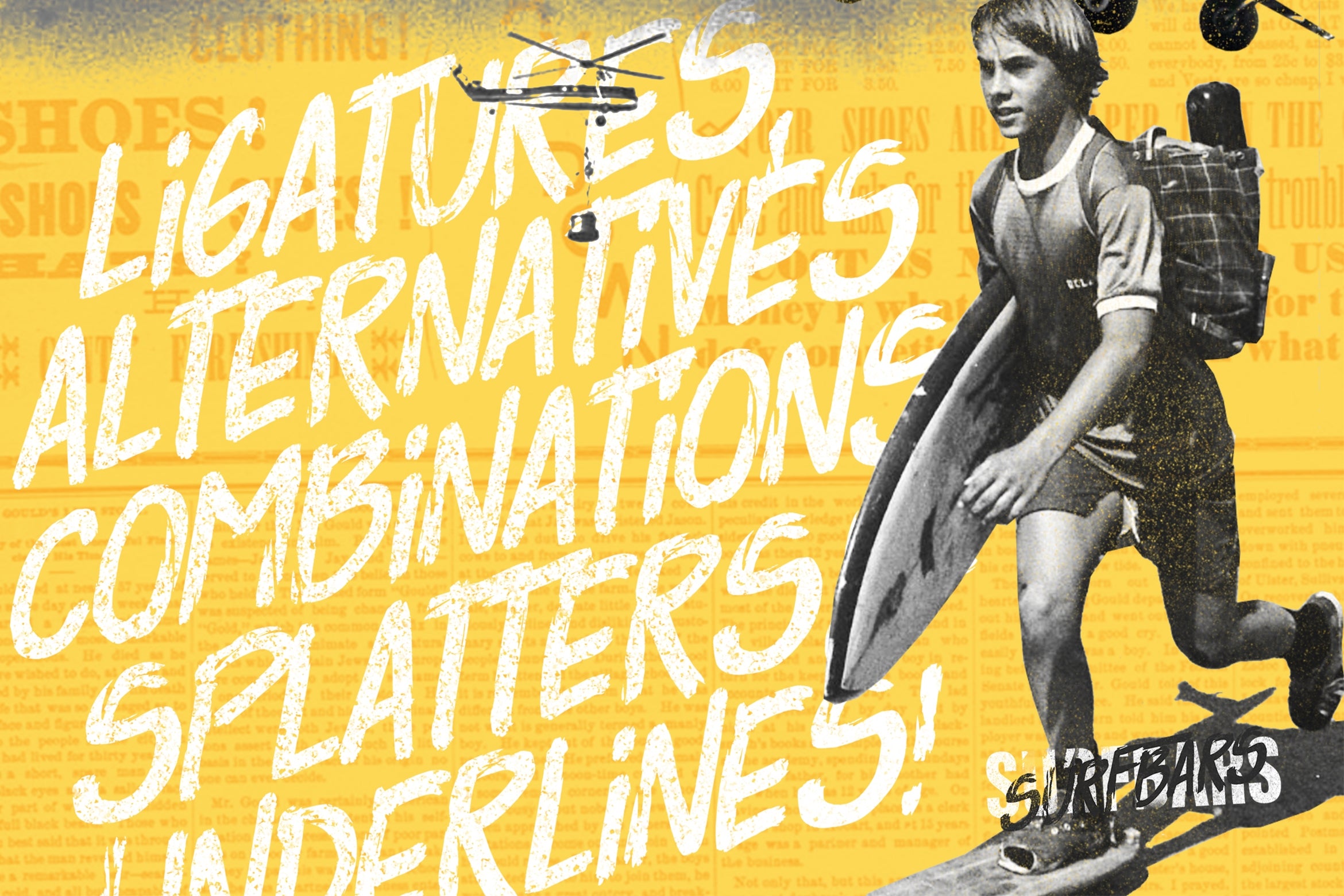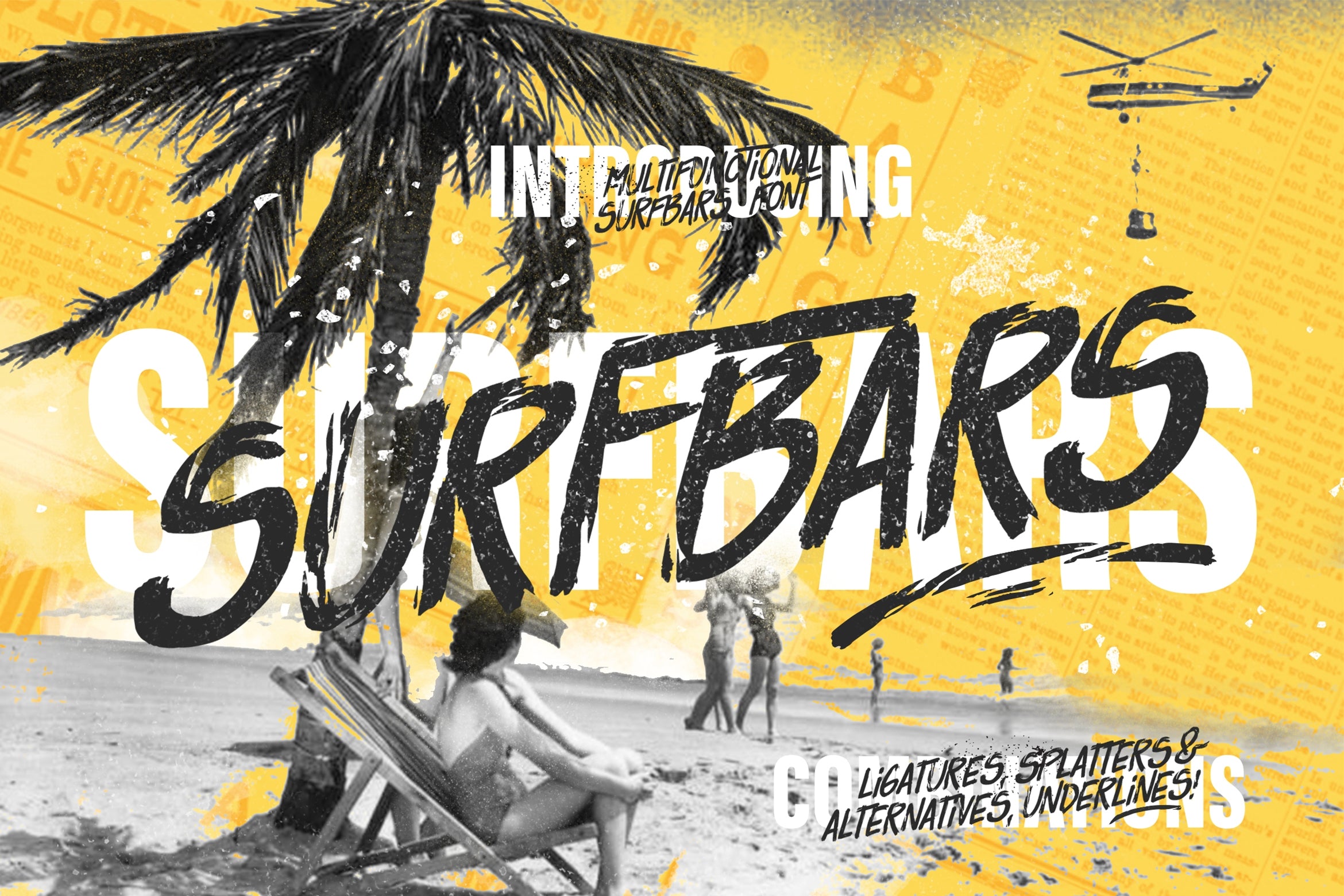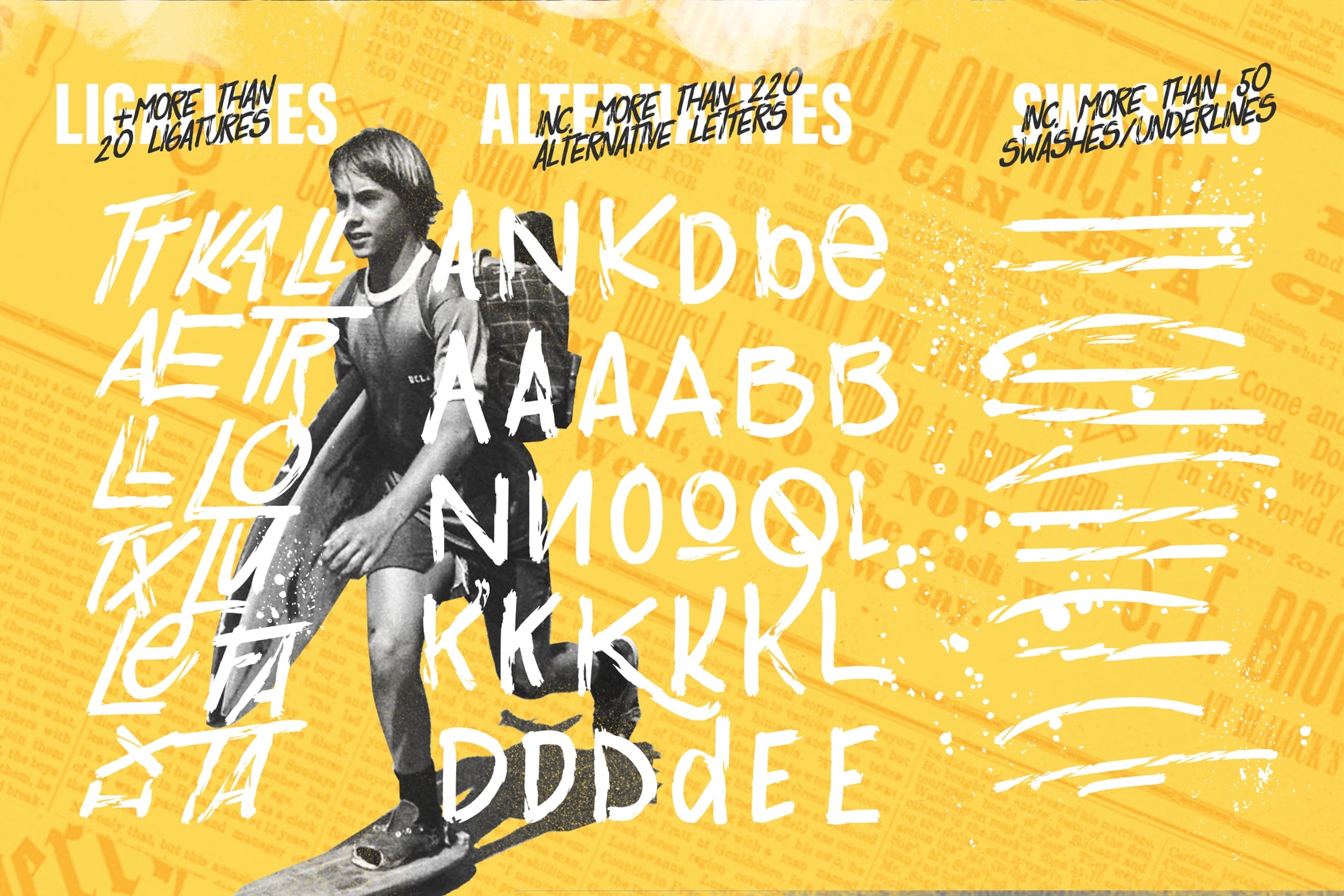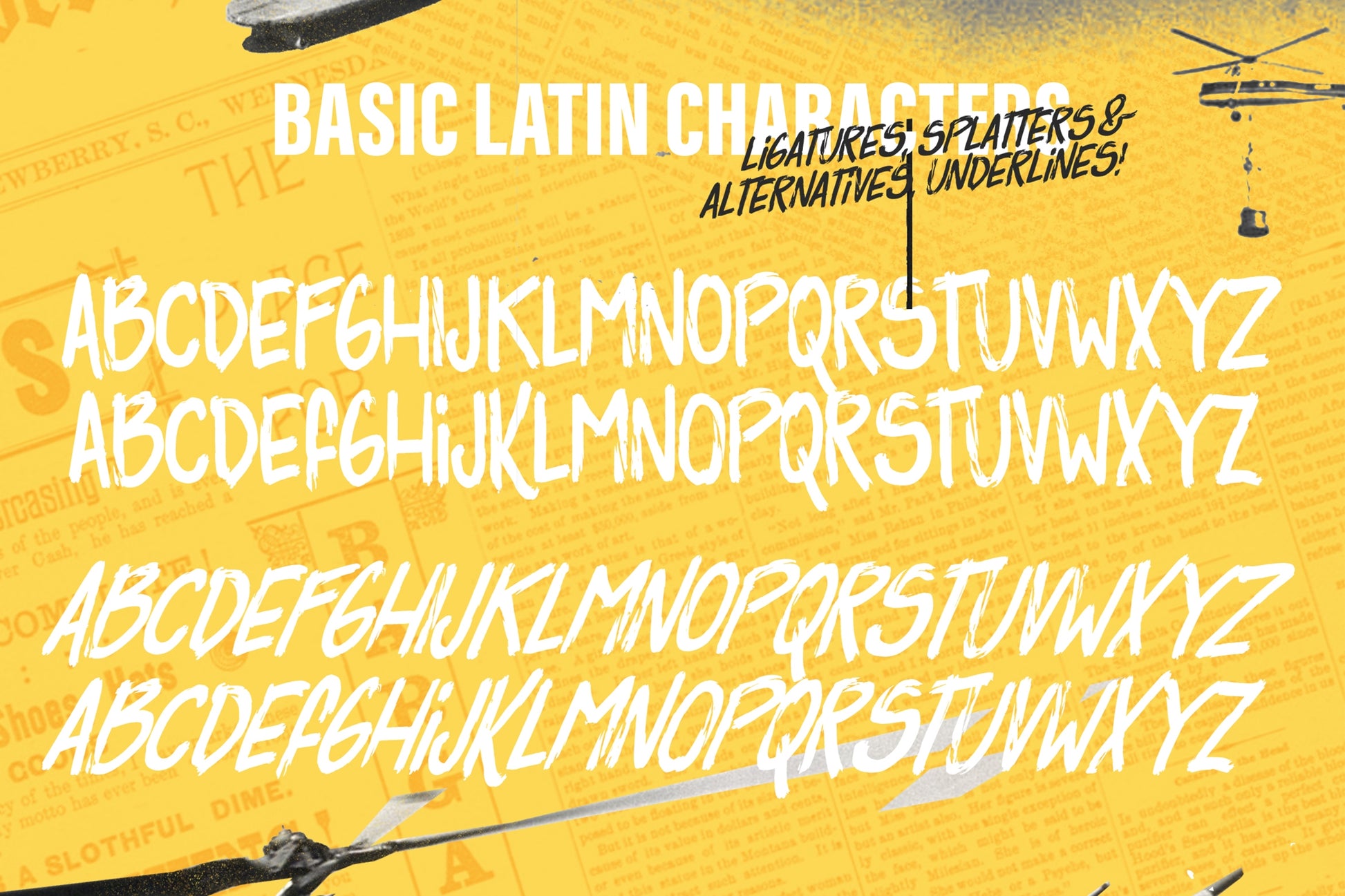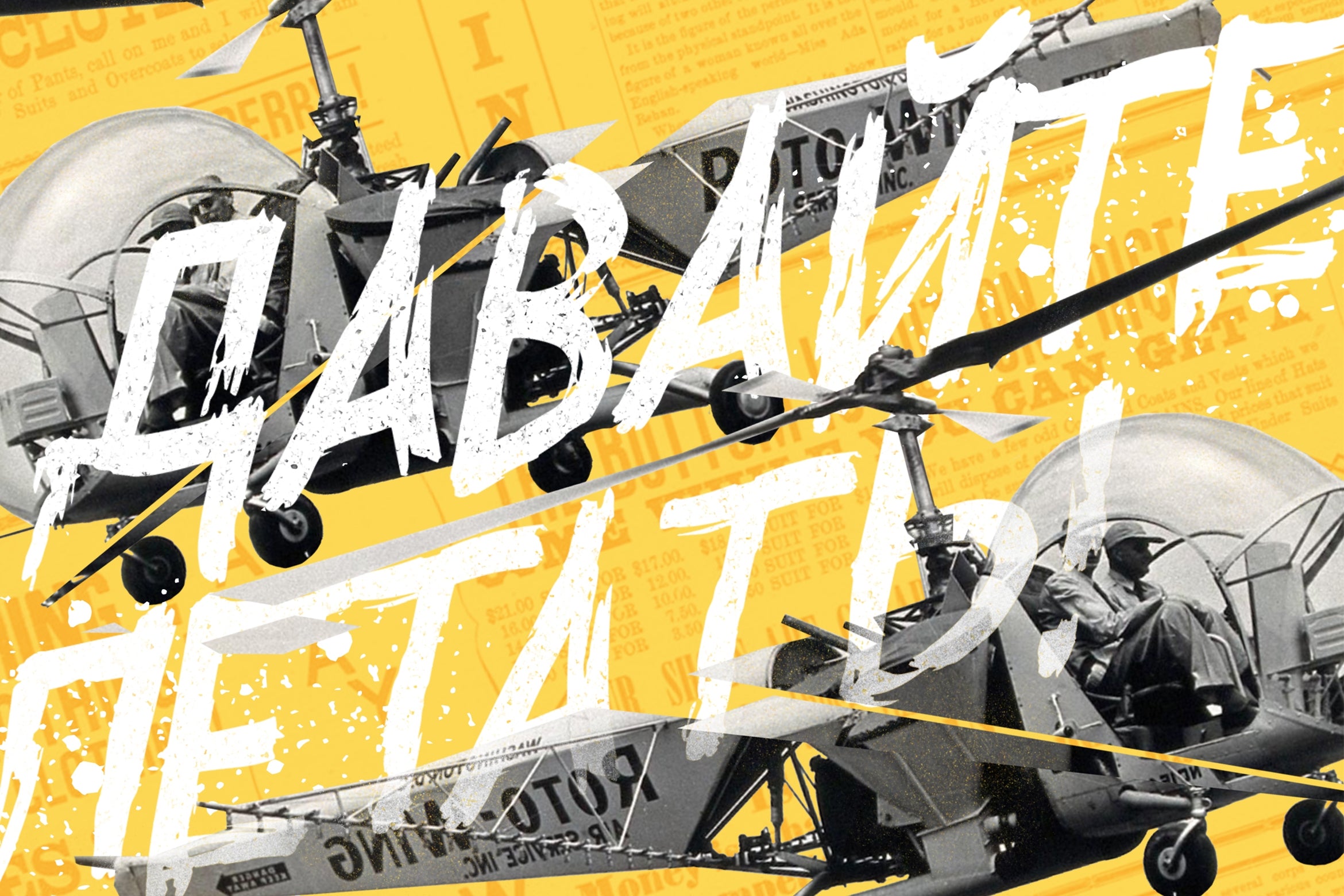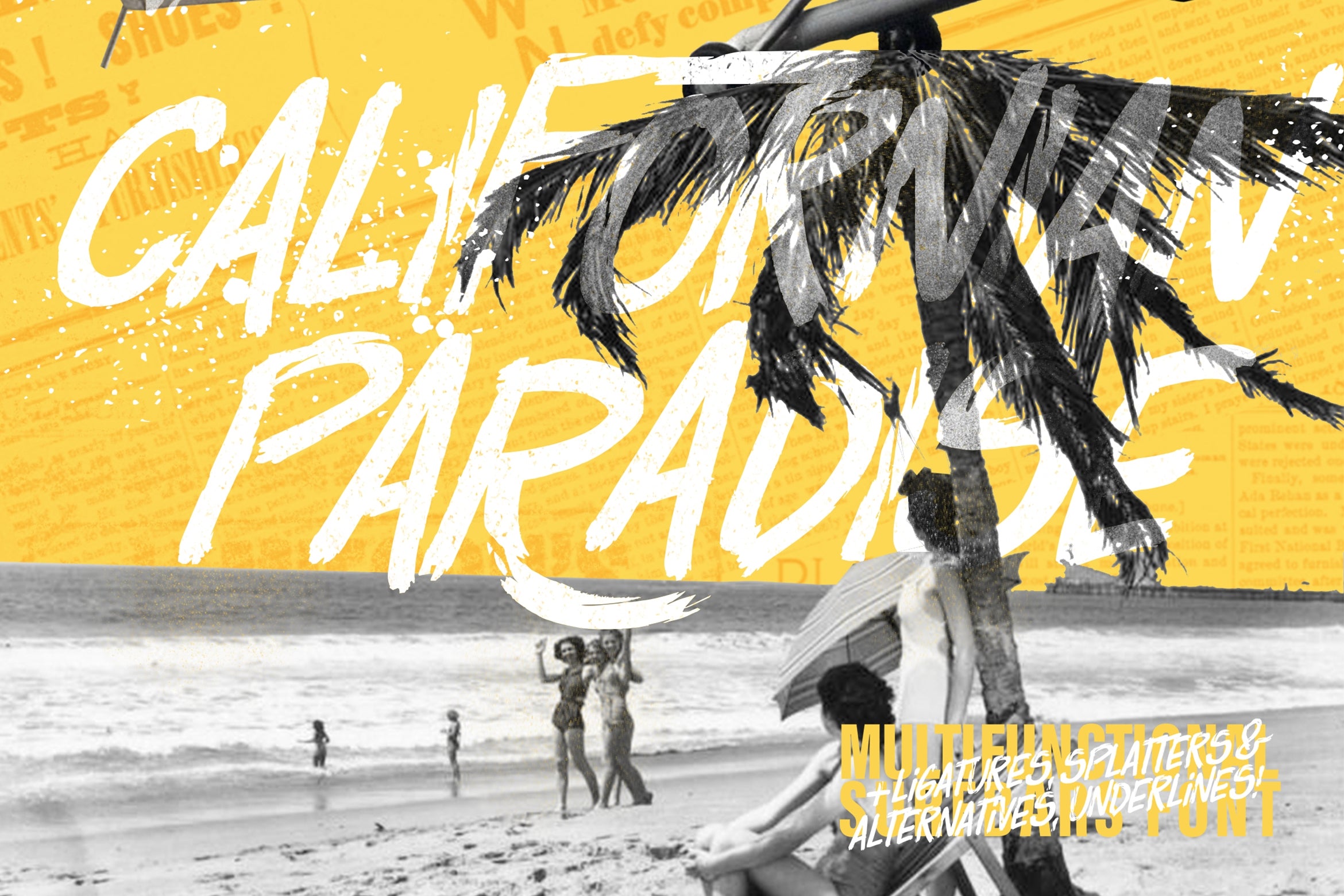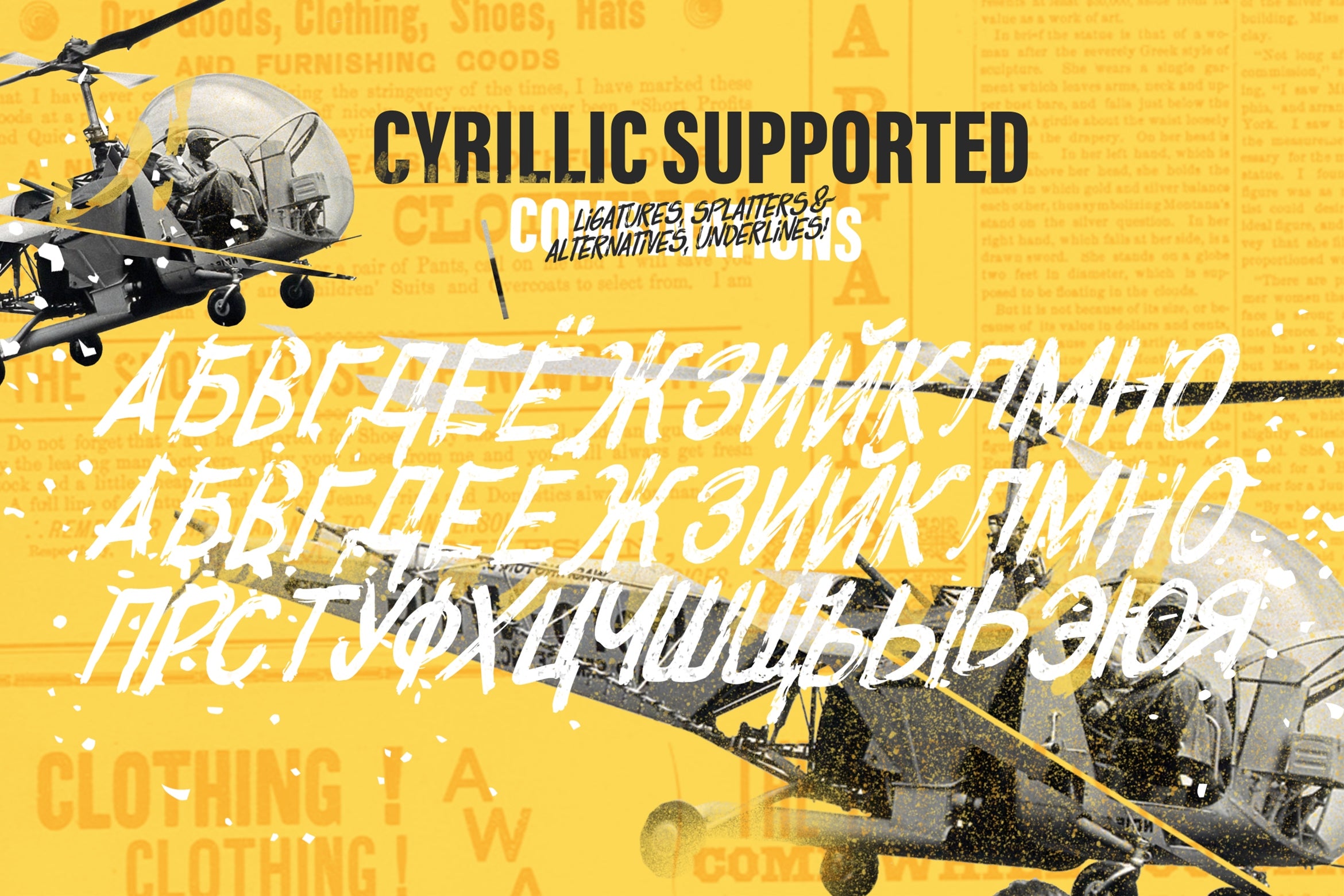
Fuente Surfbars
Surfbars es una fuente latina/cirílica multilingüe hecha a mano que se inspiró en el surf, la arena y el estilo lúdico.
Viene en Regular, Cursiva, Subrayado y Salpicado
Esta fuente incluye un conjunto completo de divertidas y únicas letras mayúsculas y minúsculas, números y una amplia gama de signos de puntuación. En total, contiene más de 760 glifos con 220 alternativas y más de 10 interesantes ligaduras, florituras y subrayados. Con esta fuente, tienes total libertad para usar y combinar diversas letras, alternativas y ligaduras, lo que te garantiza que tu diseño o cualquier proyecto será una obra maestra única.
Además, la combinación y uso de diferentes letras y ligaduras te da la oportunidad de divertirte y al mismo tiempo crear tu propio estilo único.
• Más de 760 glifos, 220 alternativas, 60 ligaduras únicas y divertidas.
• Esta fuente incluye diacríticos Latin Plus.
• Las barras de surf admiten idiomas Latin Plus (soporte para idiomas Latin Multilingual)
• Las barras de surf admiten el alfabeto cirílico.
Ideal para mensajes llamativos. Hecho con marcador plano, añadiendo movimientos realistas. Ideal para logotipos, etiquetas de nombre, citas manuscritas, empaques de productos, artículos promocionales, redes sociales y tarjetas de felicitación. También es ideal para crear diseños de camisetas y otras prendas de vestir.